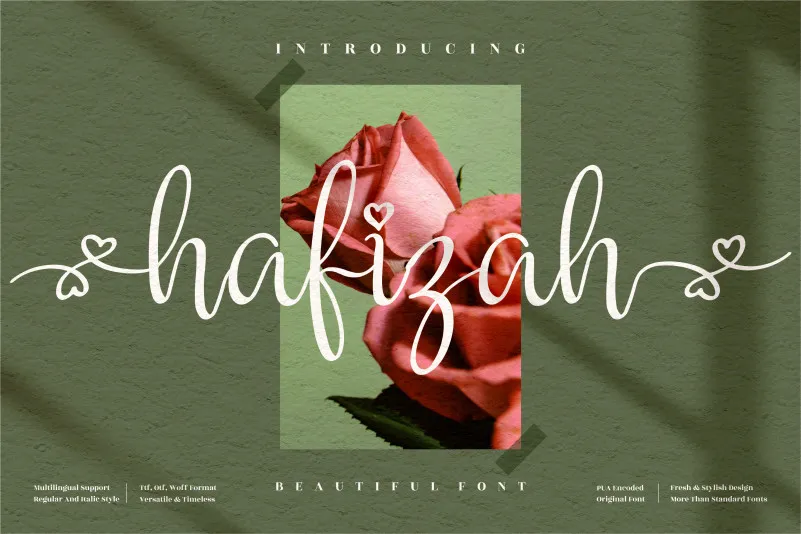
A Hafizah Font é uma encantadora escolha para os projetos que necessitam de um toque sofisticado e delicado de escrita. Perfeita para logos, identidades corporativas, design de mobiliário, embalagens de produtos, xícaras personalizadas, frases motivacionais, cartazes, sacolas de shopping, camisas personalizadas, capas de livros, cartões de nome, convites e cartões de agradecimento, etiquetas, fotografia, marca d’água para eventos especiais e qualquer outro projeto que deseje um sabor elegante da escrita. Essa fonte é tão versátil quanto a delicadeza da sua própria mão na letra. Seja você que escrever ou seja o seu design que traga vida com essa hermosa escrita. Não hesite em explorar todas as possibilidades que uma fonte de escrita oferece para iluminar qualquer projeto.